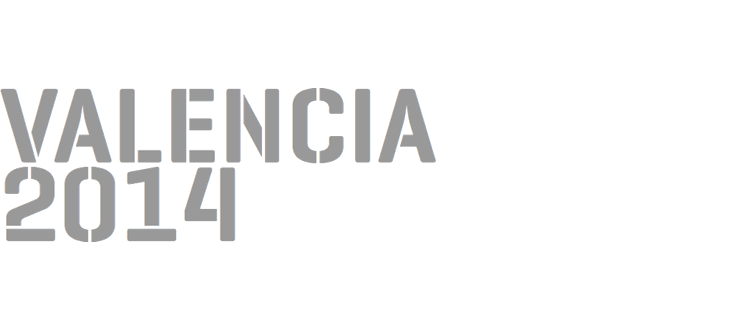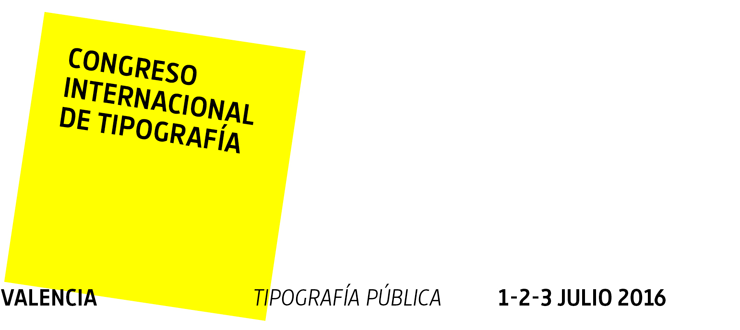
Vaya Tipo! surgió con la idea de estimular, por un lado, y dar a conocer, por otro, el trabajo de los socios de la Asociación de Diseñadores de la Comunidad Valenciana sobre el diseño de tipos.
Después de 6 años, 3 ediciones y con un colectivo mucho más maduro, “Vaya Tipo!” necesitaba encontrar nuevos caminos. Un nuevo formato totalmente diferente y el concepto de “Glocal”, para el nuevo congreso, era la evolución perfecta.
Tipos latinos, 2008. La tipografía latinoamericana es sin duda una de las más interesantes del planeta. Rigor y creatividad, además de una especial sensibilidad definida por el contexto geográfico en el que se desarrolla, caracterizan la muestra de tipos que se pudo ver en la sala ”Pecera” de la segunda planta de la ESAD.
Después de una semana loca, entre verbenas y celebraciones varias, de trabajo duro, y etc… continúo disfrutando del agradable sabor de boca que me dejó el Congreso de Tipografía. Han sido muchos los amigos reencontrados durante este evento. A algunos no los veía desde hacía mucho. Y como siempre, no quedó tiempo para todo. Así que nos quedarán las ganas de volver a Valencia, otra vez.
En mi opinión este tercer congreso —y creo que coincido con mucha gente con la que he hablado— ha situado al Congreso Internacional de Tipografía en una posición de solidez y estabilidad que habrá que saber gestionar correctamente en el futuro.
Desde mi experiencia de participación en otros congresos internacionales, os puedo asegurar que el “nuestro” (porque es de todos los que lo hacemos posible: organizadores y participantes) tiene un muy buen nivel. Además, es mucho más económico (y más generoso con las contrapartidas: fiestas, bolsa regalo, etc.). La calidad es alta porque es alto el entusiasmo y el empeño, a pesar de la falta de apoyos económicos.